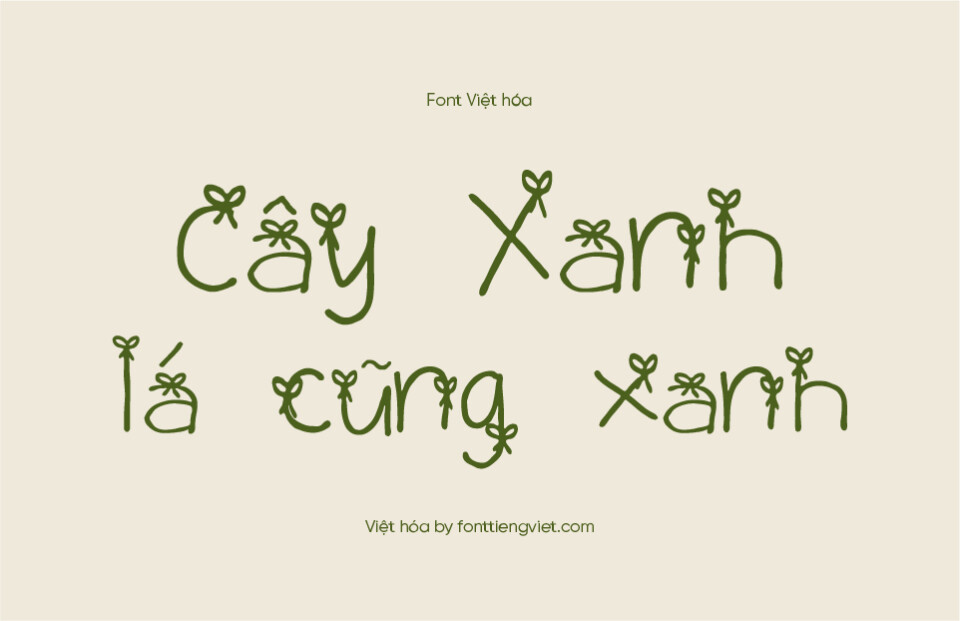
Font Việt hóa 1FTV Happy Christmas
Tải Ngay Font Việt hóa 1FTV Happy Christmas Cho Mùa Lễ Hội Ý Nghĩa
Trong không khí rộn ràng của những ngày cuối năm, việc lựa chọn một bộ Font Việt hóa 1FTV Happy Christmas phù hợp sẽ giúp các thiết kế của bạn trở nên sinh động và ấm áp hơn bao giờ hết. Đây là mẫu Font Miễn Phí được tinh chỉnh kỹ lưỡng, hỗ trợ đầy đủ bộ gõ tiếng Việt với các dấu thanh chuẩn xác, giúp người dùng dễ dàng truyền tải thông điệp yêu thương. Đối với các bạn học sinh và giáo viên, bộ font này không chỉ là công cụ trang trí mà còn là nguồn cảm hứng sáng tạo tuyệt vời cho các bài thuyết trình hay thiệp mừng Giáng sinh tự làm tại trường học.
Đặc điểm nổi bật của Font Việt hóa 1FTV Happy Christmas
Bộ font này gây ấn tượng mạnh nhờ phong cách thiết kế viết tay mềm mại, mang đậm nét thủ công và gần gũi. Từng nét chữ trong Font Việt hóa 1FTV Happy Christmas được chăm chút để tạo cảm giác vui tươi, tràn đầy năng lượng tích cực cho người xem.
Tính ứng dụng cao trong học tập và đời sống
Bạn có thể sử dụng bộ chữ này để thiết kế các bảng tin nhà trường, làm tiêu đề cho báo tường hoặc tạo ra những tấm thiệp mời dự tiệc Noel độc đáo. Nhờ khả năng hiển thị tốt trên cả màn hình máy tính và bản in, đây là lựa chọn hàng đầu cho các dự án sáng tạo không chuyên nhưng vẫn đòi hỏi tính thẩm mỹ cao.
Kết luận về bộ font chữ Giáng sinh